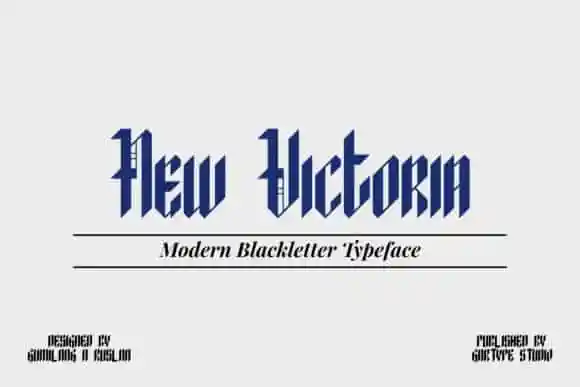
New Victoria Blackletter Font – Download Grátis
Nova Victoria Blackletter Font é uma fonte blackletter ideal para uso em títulos ou displays visivelmente chamativos. Desenvolvida pelo designer GartypeStudio a partir do universo dos cavaleiros, feitiços e palhaços, essa nova face de tipo incorpora ligaduras, minúsculas, maiúsculas e caps antigos. Seu estilo moderno mas repleto de detalhes é perfeito para usar em tamanhos grandes. Adicione esta fonte às suas ideias criativas e observe como ela as destaca! Esta nova face leva seu design a outro nível. É uma excelente opção para quem busca um toque diferenciado em sites ou materiais gráficos, tornando-os ainda mais memoráveis. A New Victoria Blackletter Font é perfeita para quem deseja um visual arredondado e elegante sem perder o charme dos antigos.